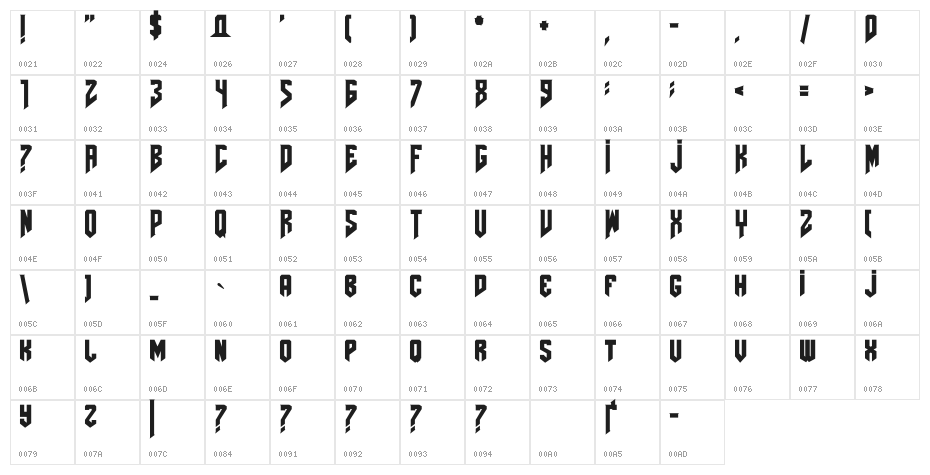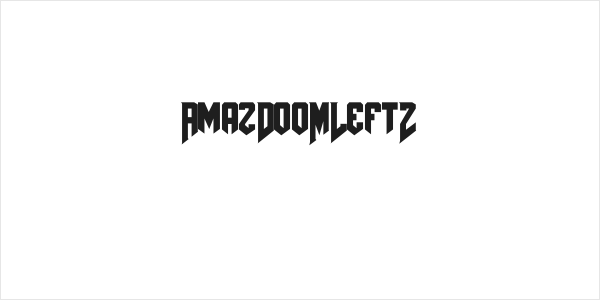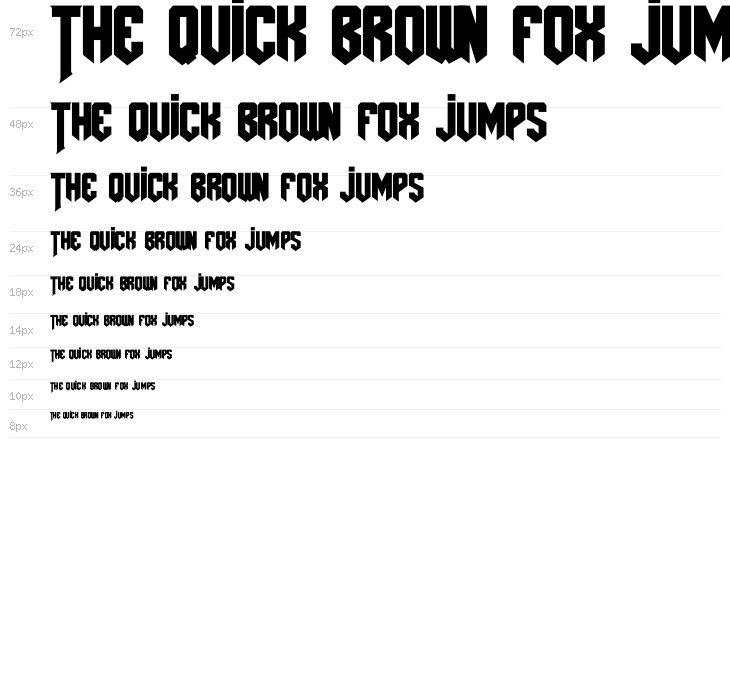
AmazDooMLeft2 Font
| Estilo general | Futuristic, Edgy |
| Proyectos propuestos | Ideal for video game titles, movie posters, branding for tech companies, or any project needing a bold, futuristic look. |